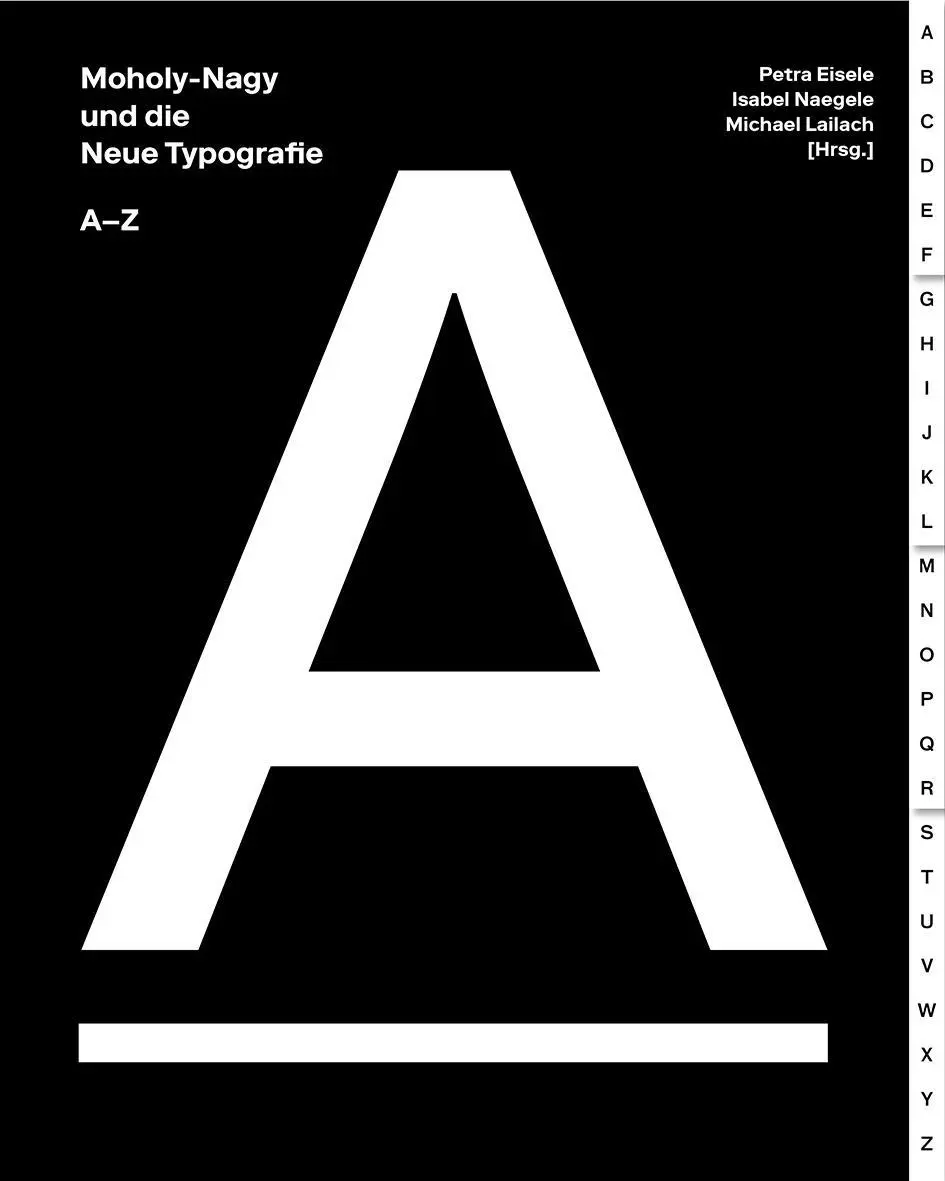
1929, zehn Jahre nach Gründung des Bauhauses, zeigte der Berliner Martin-Gropius-Bau die Ausstellung "Neue Typografie", zu der auch László Moholy-Nagy eingeladen wurde, der im Jahr zuvor Dessau verlassen und sich in Berlin einen Namen als Gestalter gemacht hatte. Für seinen Raum "Wohin geht die typografische Entwicklung?" entwarf er 78 Schautafeln zur Zukunft und Entwicklung der "Neuen Typografie" seit der Jahrhundertwende. Für seine Tafeln verwendete Moholy-Nagy sowohl eigene Entwürfe als auch Werbedrucksachen von Kollegen aus dem Bauhaus-Umfeld.
Mit dem funktionalen Grafikdesign der "Neuen Typografie" hatte sich in den 1920er-Jahren eine künstlerische Reklamegestaltung durchgesetzt, die mit der bisherigen Tradition brach. Ziel war eine zeitgemäße Gestaltung mit standardisierten Schrifttypen, industriellen DIN-Normen und Idealen wie Lesbarkeit, Klarheit und Direktheit entsprechend den Prinzipien der konstruktivistischen Kunst.
Die umfangreiche Publikation vereint erstmals die vor kurzem in der Berliner Kunstbibliothek wiederentdeckten Ausstellungstafeln von Moholy-Nagy, die anhand eines "Abcdariums" mit charakteristischen Stichworten von namhaften Autor*innen beleuchtet werden - von A wie Asymmetrie bis Z wie Zukunftsvision. Durch assoziierendes Querlesen wird so der typografische Ideenkosmos der Avantgarde der 1920er-Jahre wieder erfahrbar.